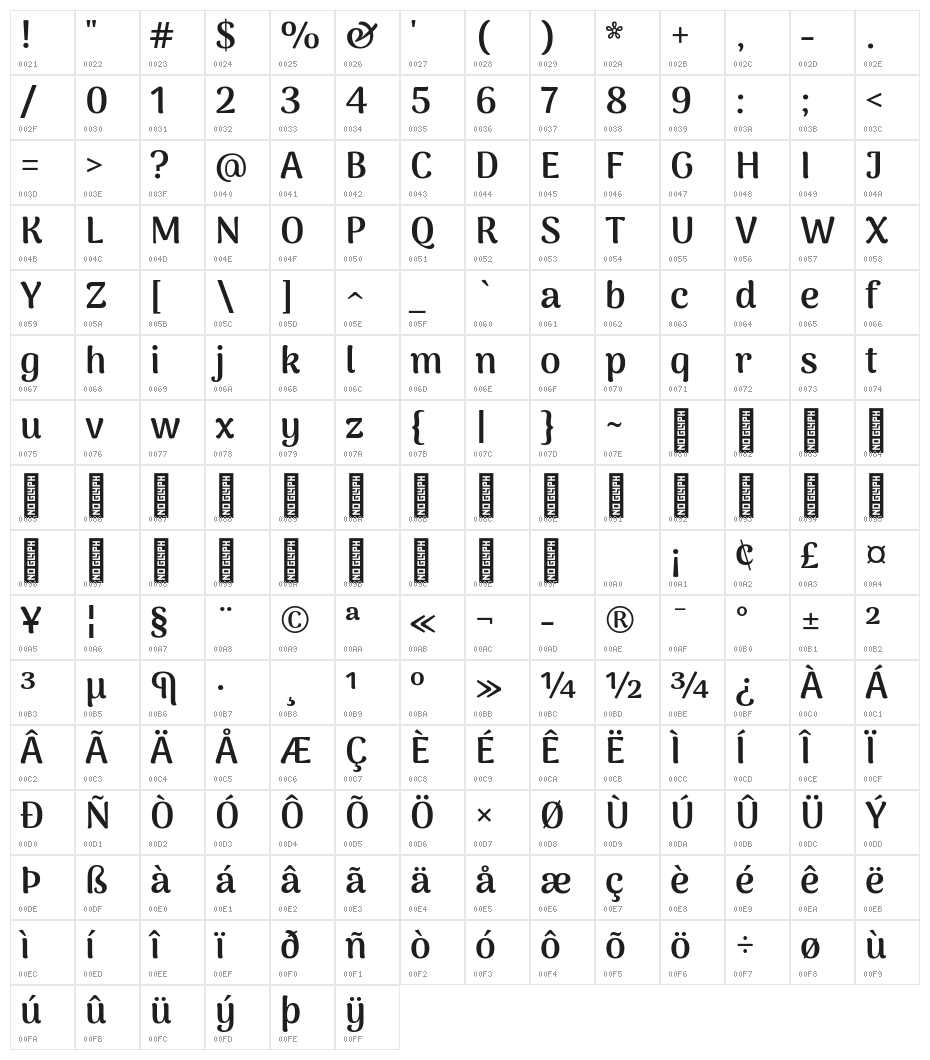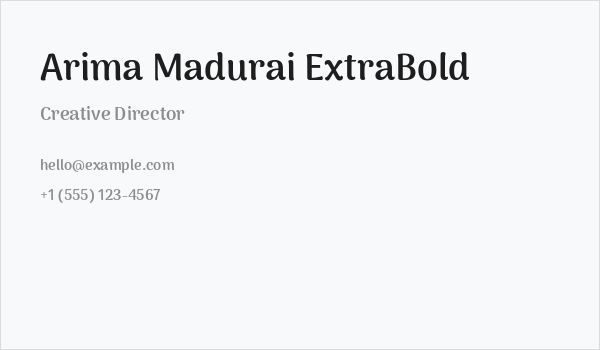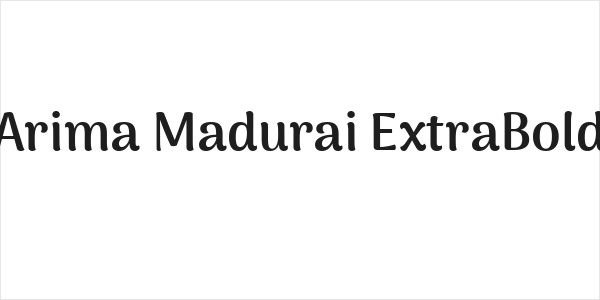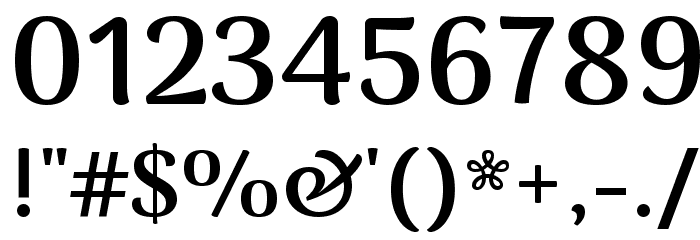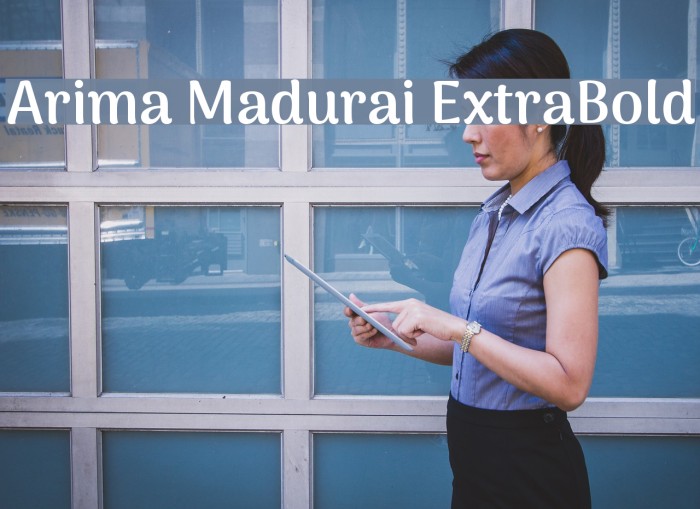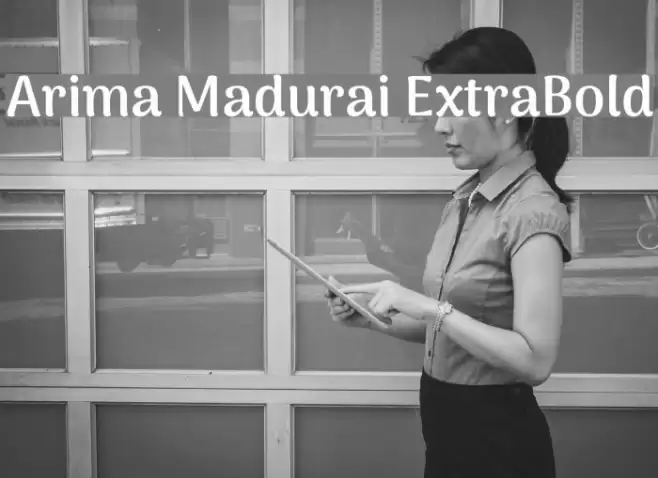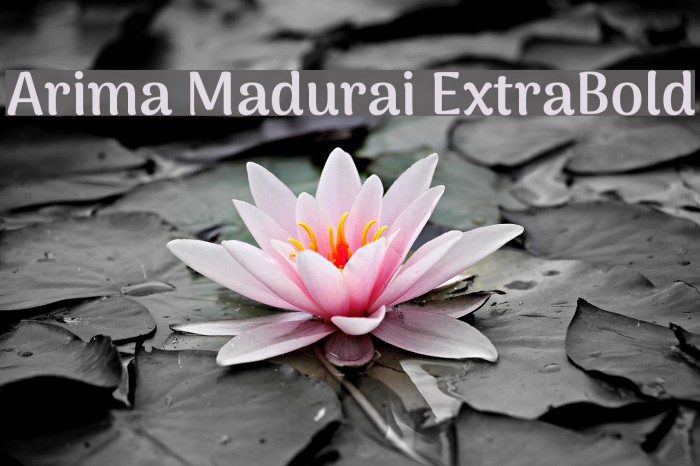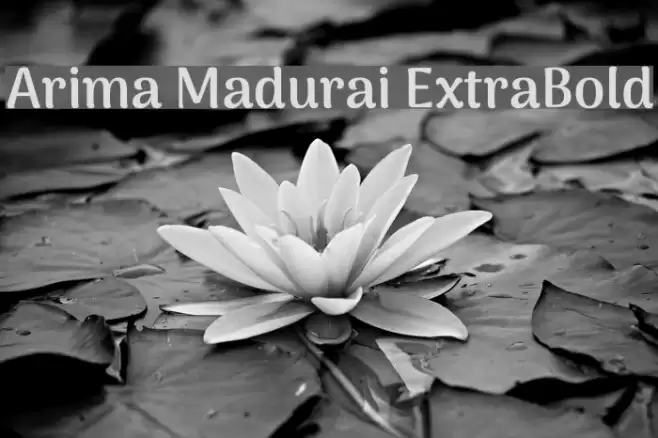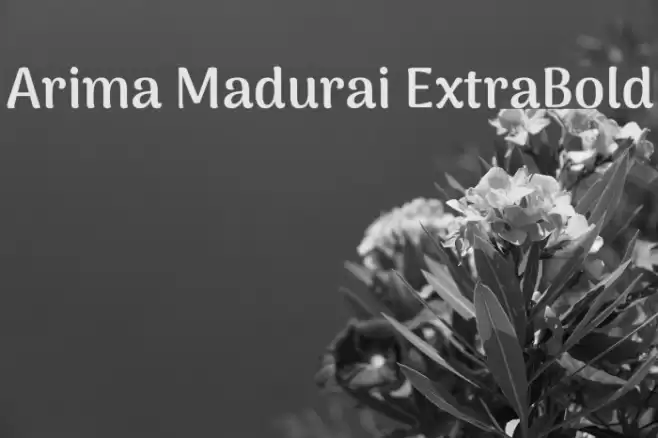
Arima Madurai ExtraBold Font
| Projets proposés | Ideal for branding, headlines, posters, and digital media where a strong and friendly presence is desired. |